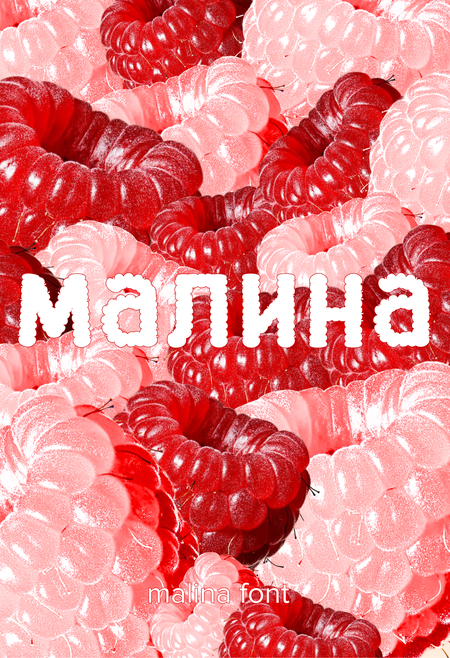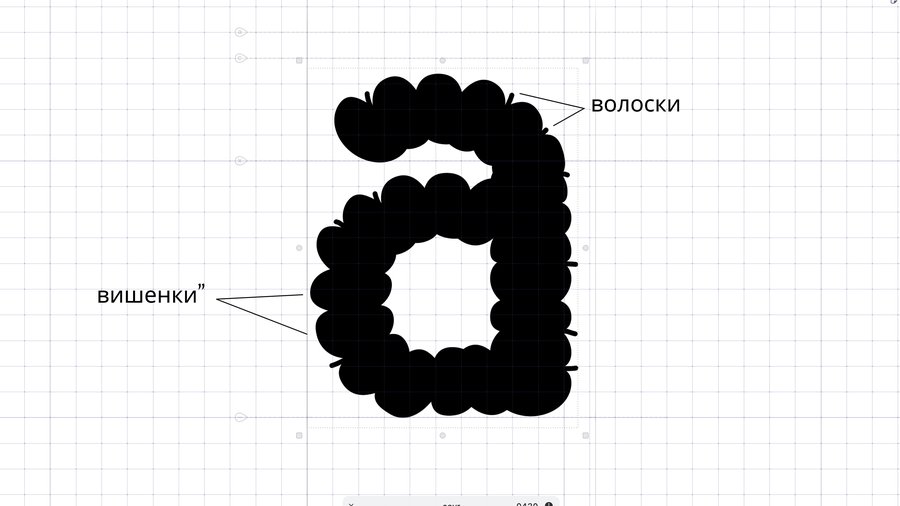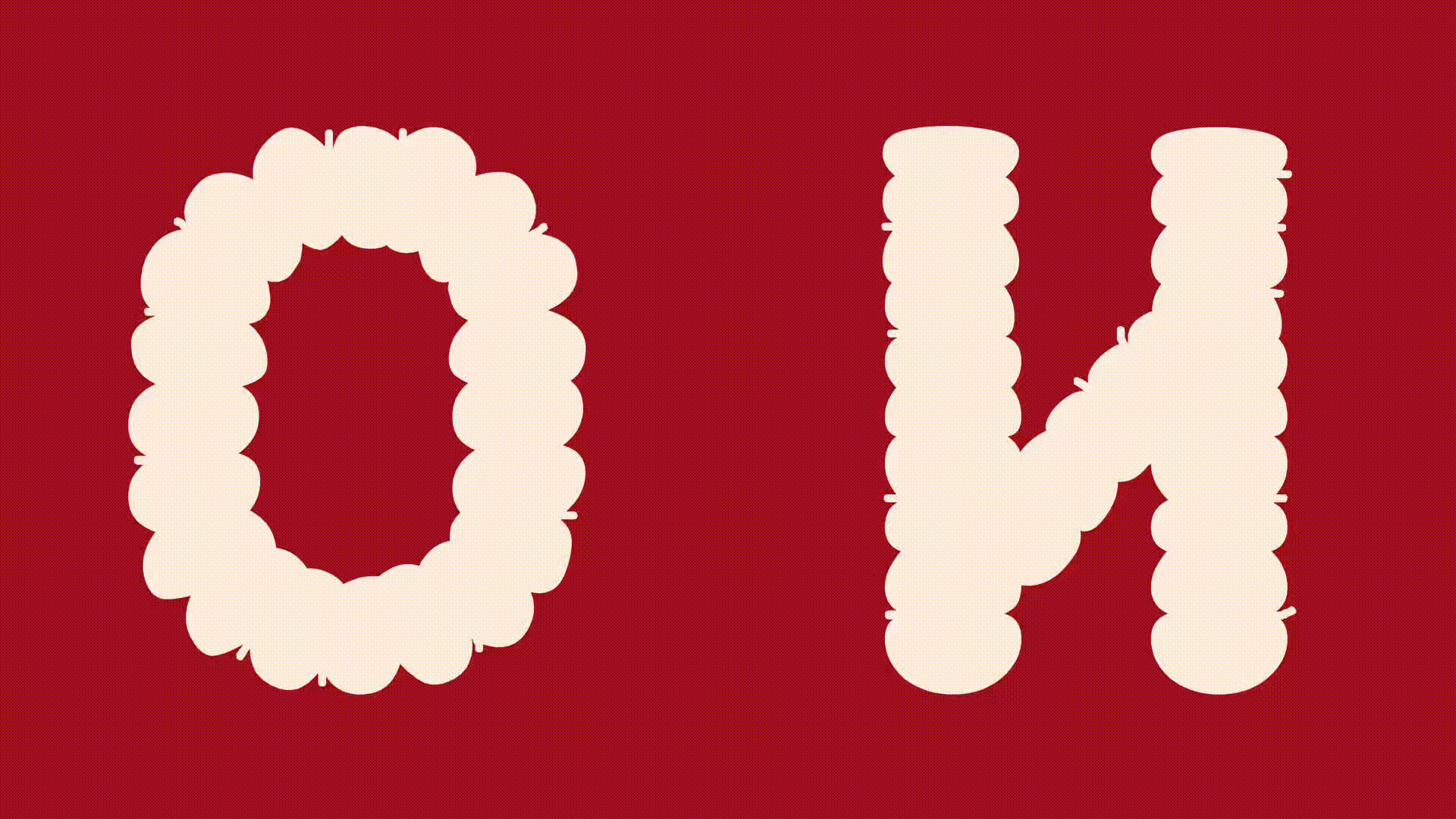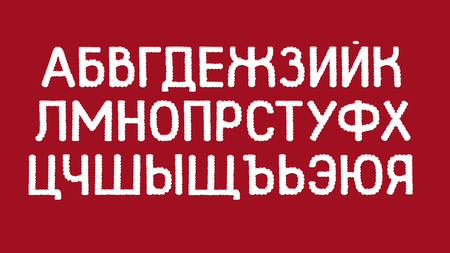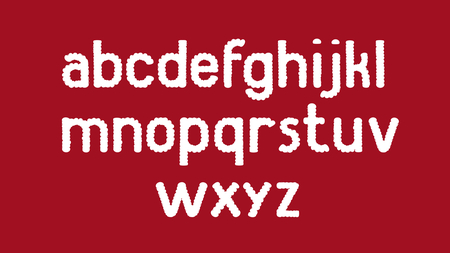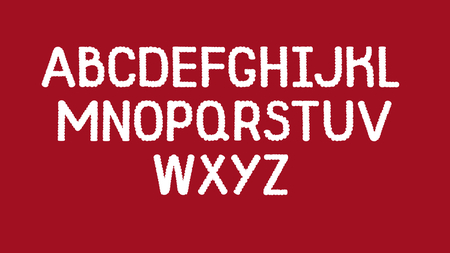
Шрифт вдохновлён малиной и её строением
референс
Буквы собраны из отдельных округлых элементов, по принципу строения ягоды
Шрифт не копирует образ малины напрямую, а повторяет её структуру — благодаря этому форма выглядит естественно и не перегружена декоративными деталями
кириллица
латиница
знаки и цифры
Rasberry — намеренно упрощённая форма слова raspberry. Пропуск буквы отражает ручной характер бренда, подчёркивает, что здесь важны не правила, а вкус, форма и ощущение.